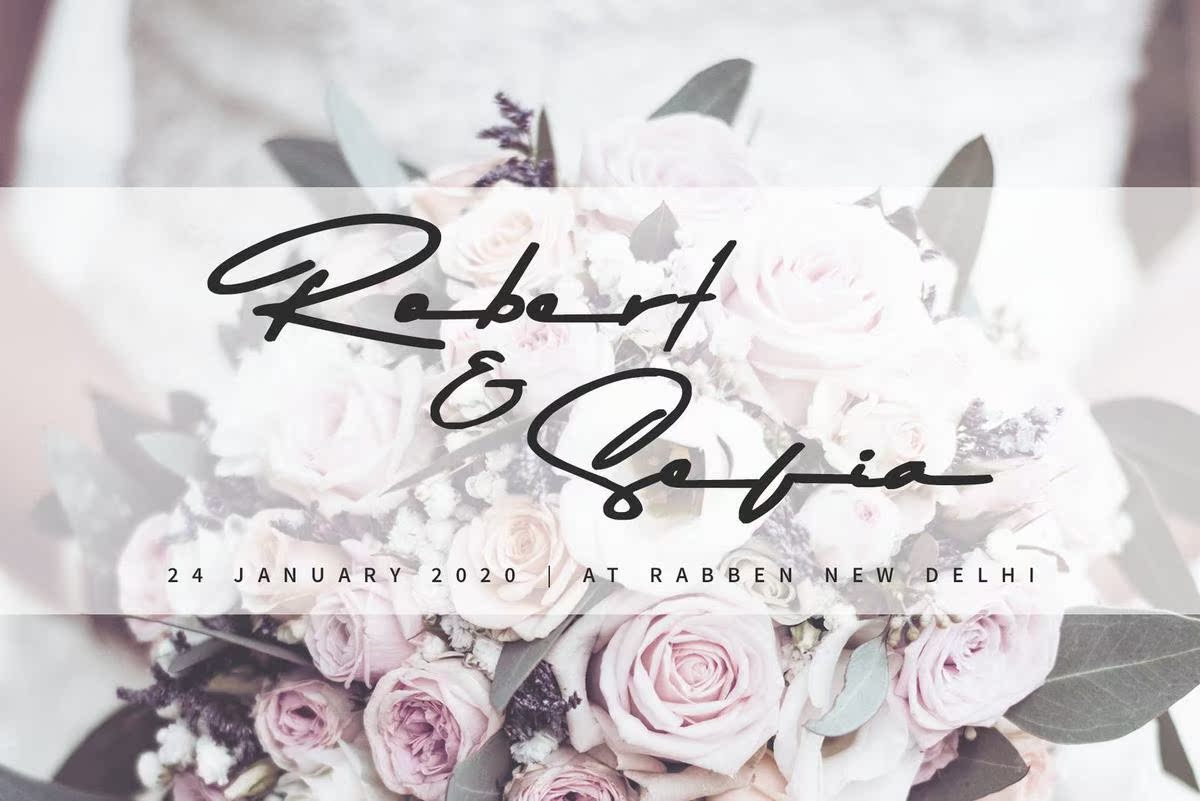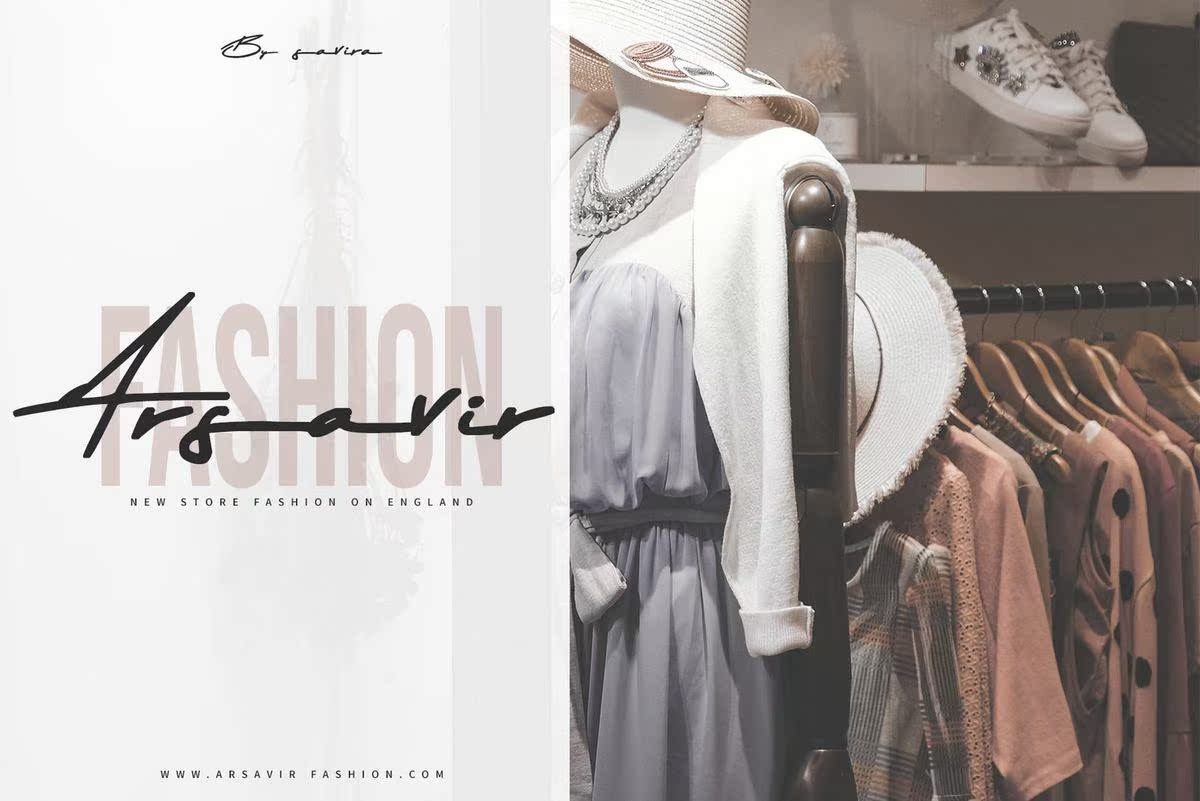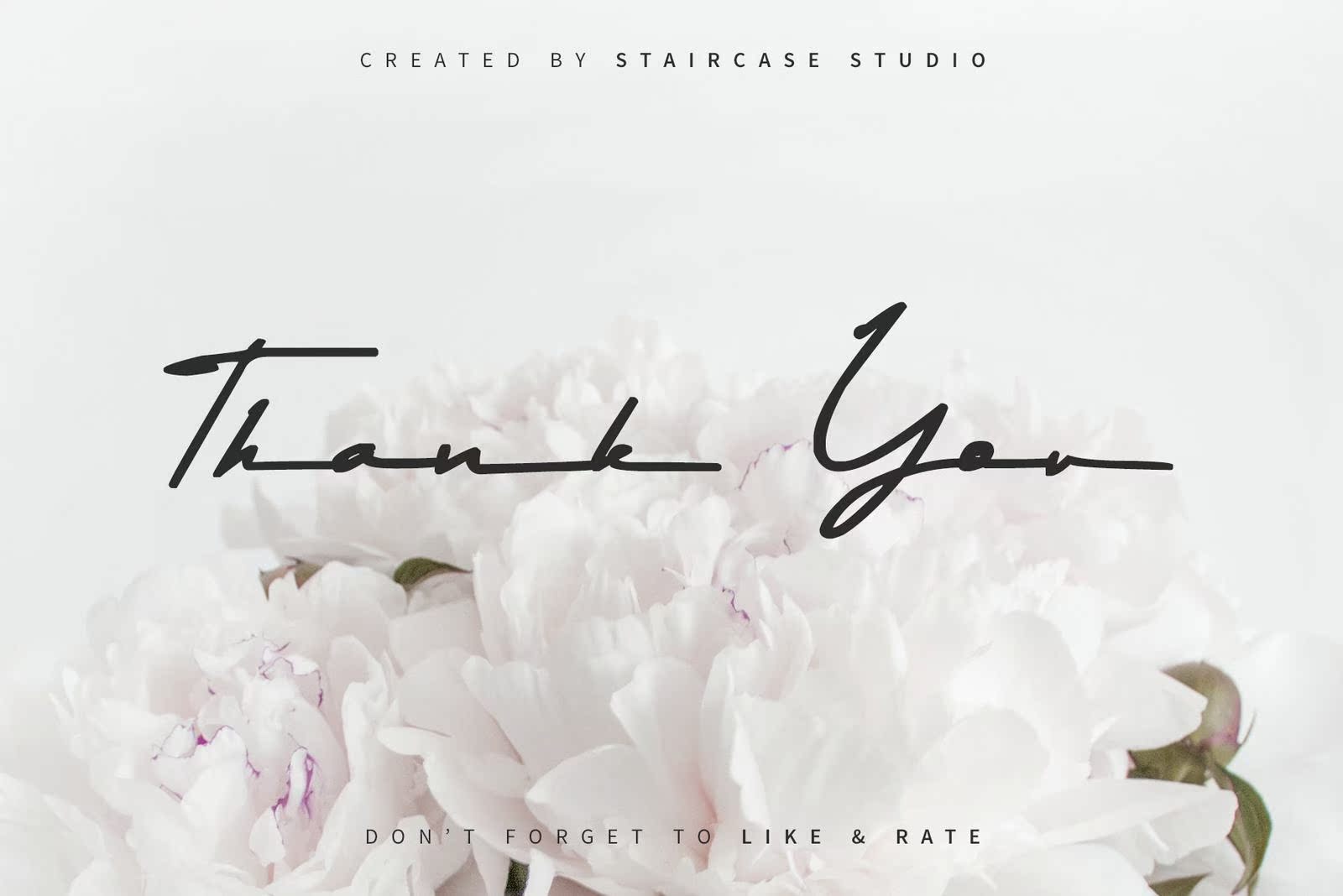
Gilberta手写字体签名。适合您项目的文字和数字的集合非常适合于标识、品牌设计、标志设计、数字刻字艺术、T恤/服装、海报、杂志、标志、广告设计和任何设计需求。Gilberta手写字体签名。适合您项目的文字和数字的集合非常适合于标识,品牌设计、标志设计、数字文字艺术、T恤/服装、海报、杂志、标志、广告设计和任何设计需求。